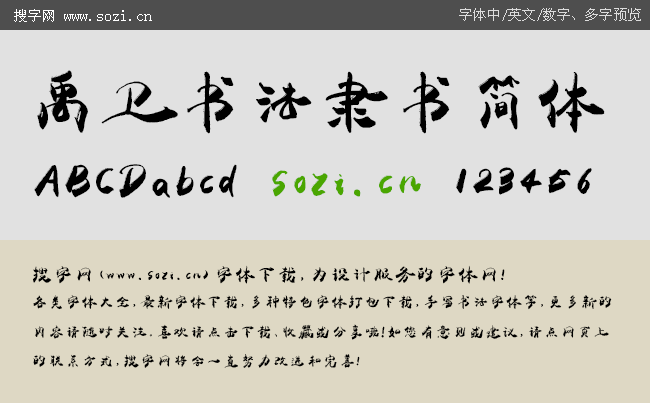
禹衛(wèi)書(shū)法隸書(shū)簡(jiǎn)體
搜字網(wǎng)給大家提供一款禹衛(wèi)書(shū)法隸書(shū)簡(jiǎn)體中文書(shū)法字體下載。該字體凝重典雅,古樸莊重,具有濃厚的古典氣息,適合包裝設(shè)計(jì)、海報(bào)設(shè)計(jì)、畫(huà)冊(cè)設(shè)計(jì)等廣告設(shè)計(jì)場(chǎng)合使用。